В сегодняшней статье мы рассмотрим несколько важнейших принципов из книги Эллен Луптон «Шрифтовое мышление» (Thinking with Type) и узнаем, как перевести нашу работу со шрифтами на следующий уровень.
Типографика повсюду — на сайтах, упаковках, в рекламе, книгах и даже мемах. Однако слишком часто мы упускаем из виду ее истинную силу.
Шрифты — это не просто буквы, это молчаливые продавцы, амбассадоры вашего бренда, которые рассказывают его историю.
В книге Эллен Луптон «Шрифтовое мышление» (Thinking with Type) показано, какой преображающей силой может обладать отличная типографика. Сегодня мы рассмотрим несколько важнейших принципов из этой книги и узнаем, как перевести нашу работу со шрифтами на следующий уровень.
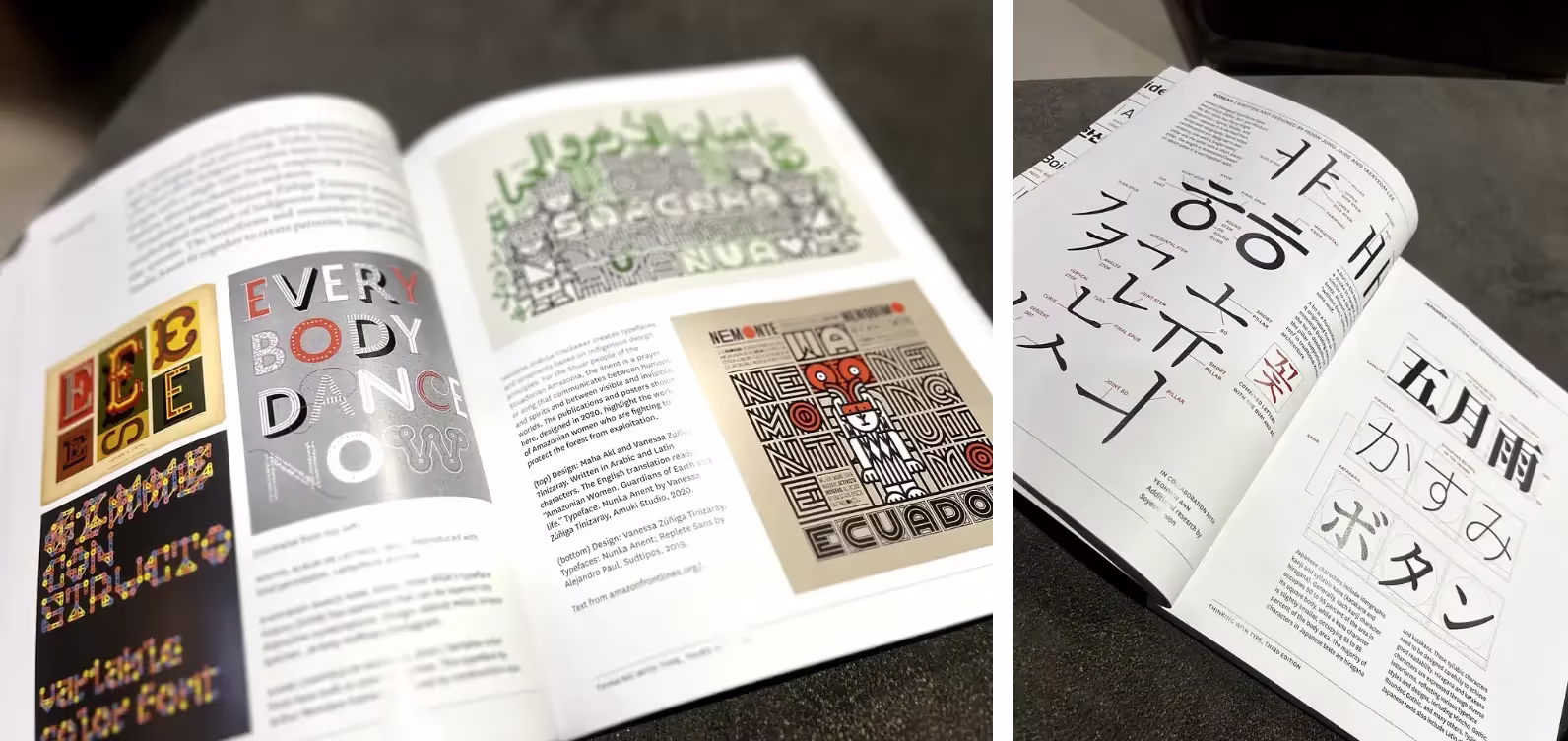
1. Искусство сочетания шрифтов: баланс между хаосом и гармонией
Подбор шрифтовых пар можно сравнить с организацией званого ужина. 🍽 🍽🍽 Правильная комбинация создаст оживленную беседу, но если вы позовете слишком много громких личностей, за столом начнется настоящий хаос.
Что же предлагает Эллен Луптон? Следовать принципам контраста и дополнения.
Шрифтовые пары создают визуальный интерес и помогают управлять вниманием аудитории. Они могут:
- Устанавливать четкую иерархию (например, жирный шрифт для заголовков, обычный — для основного текста).
- Передавать сразу несколько эмоций (например, игривые заголовки и строгий, профессиональный контент).
- Отражать разные характеристики бренда (современный, но классический? игривый, но серьезный?).
Но помните, меньше — значит больше. Используйте два шрифта — или три, если вы чувствуете себя авантюристом.
Как сочетать шрифты
1. Создайте контраст: Противоположности притягиваются. Классическое сочетание, которое никогда не выходит из моды, — шрифт с засечками + шрифт без засечек.
Пример: Garamond (шрифт с засечками) + Helvetica (шрифт без засечек).
Почему это работает: Шрифты с засечками кажутся традиционными, а шрифты без засечек — чистыми и современными. Они уравновешивают друг друга.
2. Думайте о пропорциях: Ищите шрифты с одинаковой высотой строчных букв (x-height) и межстрочным расстоянием.
Строчные буквы одинаковой высоты хорошо сочетаются друг с другом, даже если в целом шрифты совсем не похожи.
И напротив, если высота строчных букв различается слишком сильно, это может затруднить чтение и восприятие текста. Одинаковая x-height создает баланс — шрифты достаточно контрастны, чтобы их можно было мгновенно дифференцировать, но при этом гармонично смотрятся вместе. Эта простая деталь может существенно повлиять на то, насколько эстетичным и читаемым будет ваш дизайн.
Пример: Playfair Display (шрифт с засечками) + Source Sans Pro (шрифт без засечек).
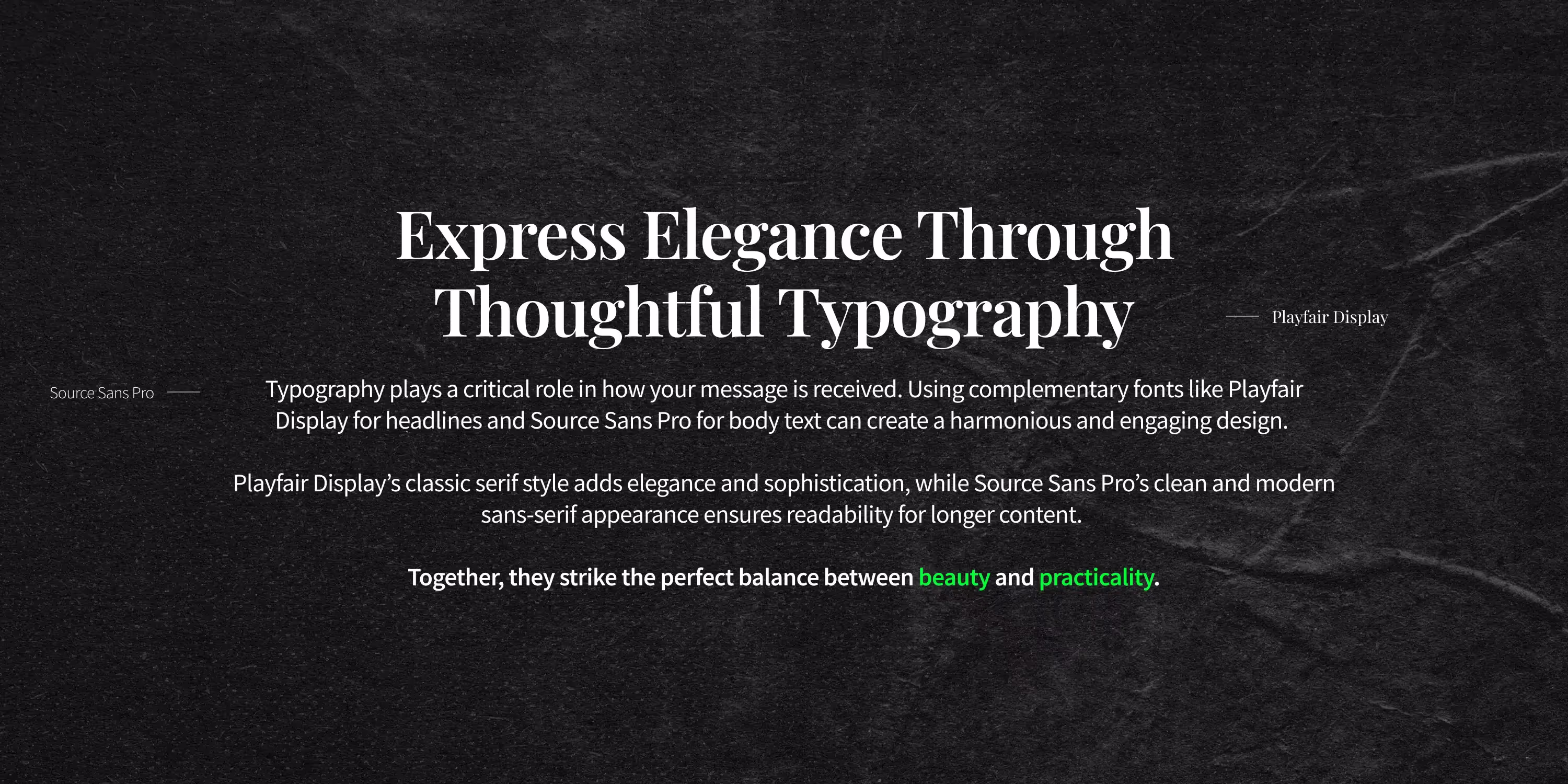
3. Подберите настроение: Шрифты должны соответствовать тону вашего сообщения. Пишете о технологическом стартапе? Выбирайте минималистичные гротески. Оформляете свадебные приглашения? Рукописный шрифт типа Pacifico придаст дизайну элегантности.
4. Держите в голове послание бренда: Допустим, вы разрабатываете дизайн для юридической фирмы. Классический шрифт с засечками для заголовков (например, Times New Roman) в сочетании с современным шрифтом без засечек (например, Arial) для основного текста говорит: «Мы опираемся на традиции, но принимаем инновации».
Вот несколько проверенных временем шрифтовых пар:
Классическое сочетание: Georgia + Open Sans
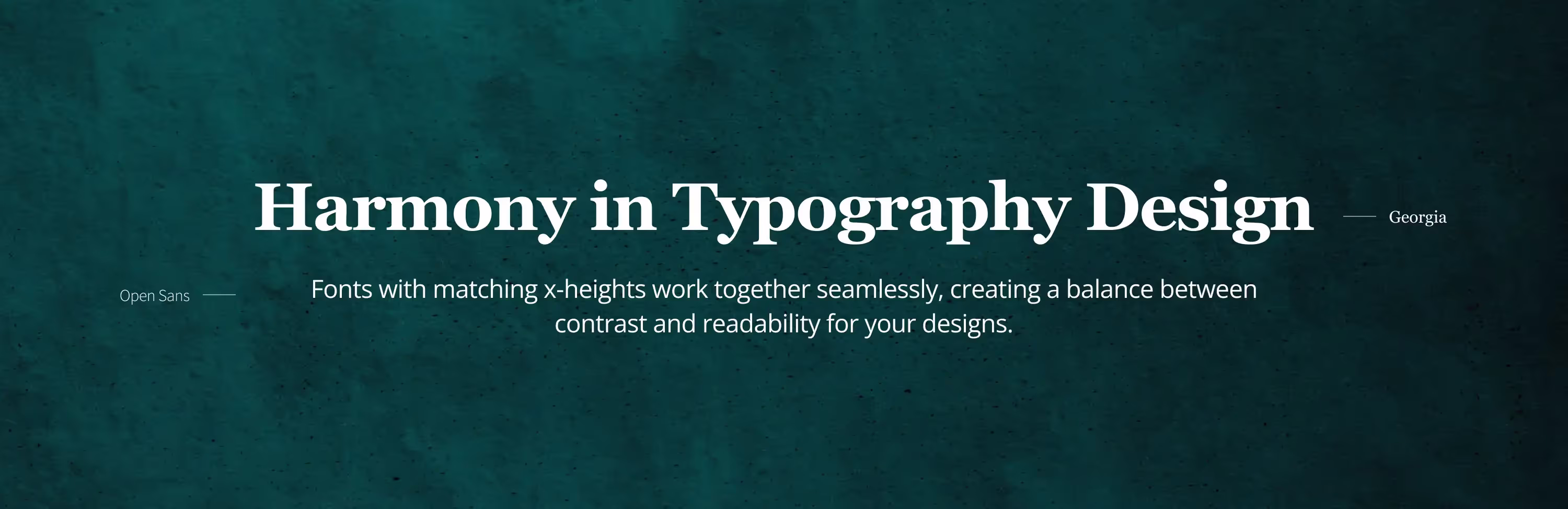
Современный минимализм: Montserrat + Lato
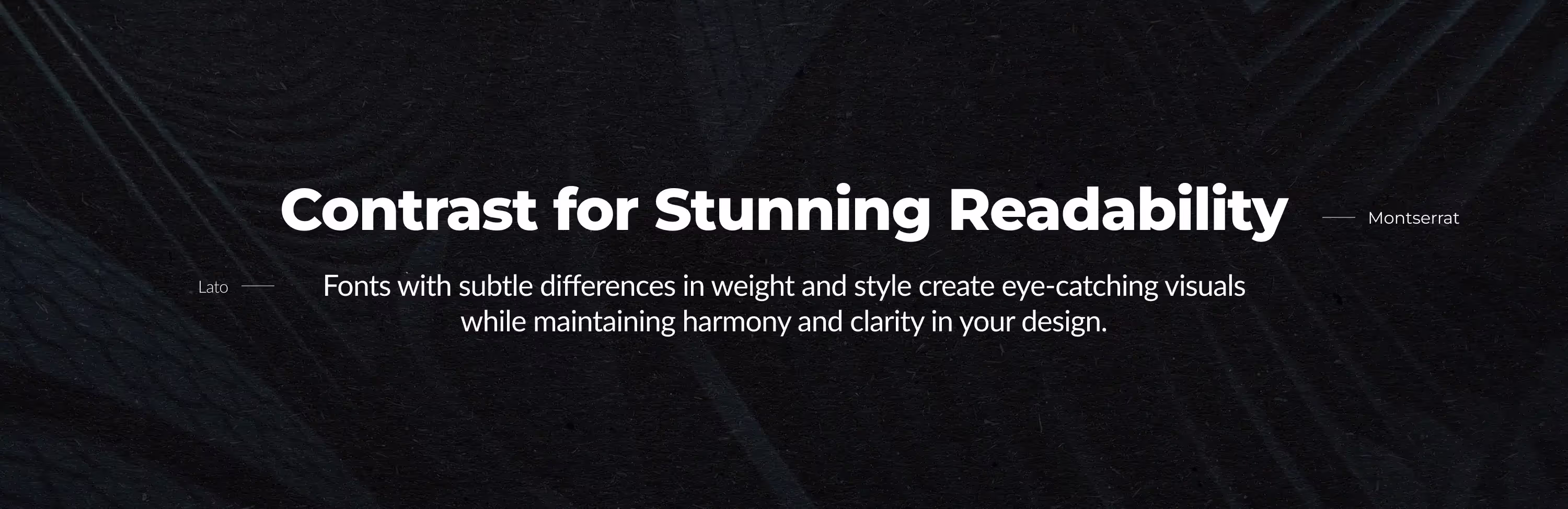
Игривая пара: Lobster + Raleway
Помните: цель не в том, чтобы каждый из шрифтов выделялся и перетягивал на себя внимание, а в том, чтобы они гармонично сочетались друг с другом.
2. Типографика как амбассадор бренда
Шрифты — это не просто визуальные элементы, это эмоциональные сигналы.
Подумайте о своих любимых брендах. О чем говорят их шрифты? Изящный гротеск Apple просто кричит о современности, а антиква The New York Times — об авторитете и традициях.
Шрифт во многом формирует первое впечатление о бренде. Он говорит аудитории:
- Что это за бренд: Профессиональный или дружелюбный? Сдержанный или смелый?
- Какие ценности он разделяет: Традиции, творчество или инновации?
- Какие чувства он вызывает: Доверие, воодушевление или любопытство?
Как создать целостную идентичность бренда:
1. Будьте последовательны: Используйте одни и те же шрифты на всех платформах — на сайте, в соцсетях, в печатных материалах. Это повысит узнаваемость бренда.
2. Тестируйте шрифты на разных носителях и устройствах: Шрифты, которые отлично смотрятся в печати, могут плохо выглядеть на экране смартфона.
3. Меняйтесь осмысленно: Бренды растут и развиваются, как и их типографика. Отказ Google от шрифта с засечками в пользу гротеска в 2015 году отразил стремление компании к простоте и адаптивности. Обратите внимание, технологический гигант не отрекся от своей сути — лишь модернизировал ее.
- Избегайте сочетания двух рукописных шрифтов или двух жирных шрифтов — такой дизайн будет выглядеть слишком драматичным и перегруженным.
Заключение
Типографика — это не просто элемент эстетики. Она должна усиливать бренд и доносить до аудитории ваше сообщение.
Независимо от того, разрабатываете ли вы веб-сайт, создаете плакат или запускаете новое приложение, правильная типографика способна привлечь внимание, вызвать доверие и даже побудить к действию.
Начните экспериментировать, и пусть ваша типографика говорит сама за себя!